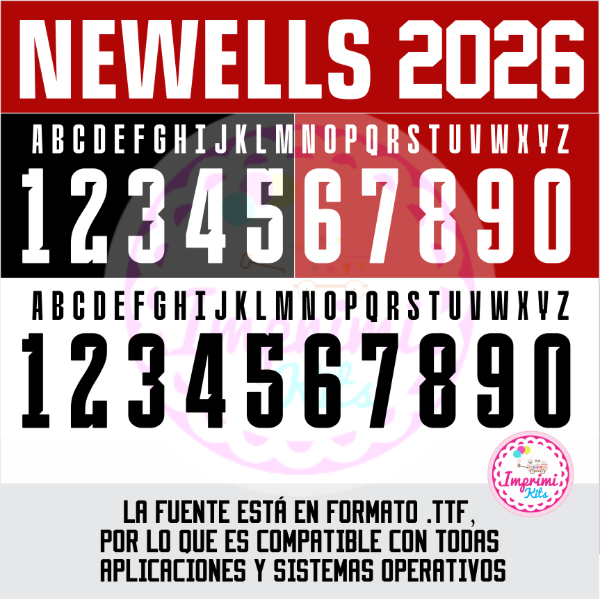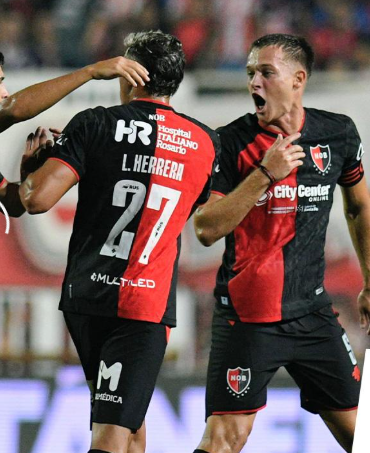
NUEVA! Tipografía Números Fuente Camisetas 2026 NEWELL´S OLD BOYS
NEWELLS
Tipografía Números Fuente 2026 NUEVA EQUIPACIÓN
Realizá todo tipo de creaciones con la tipografía utilizada actualmente en el club